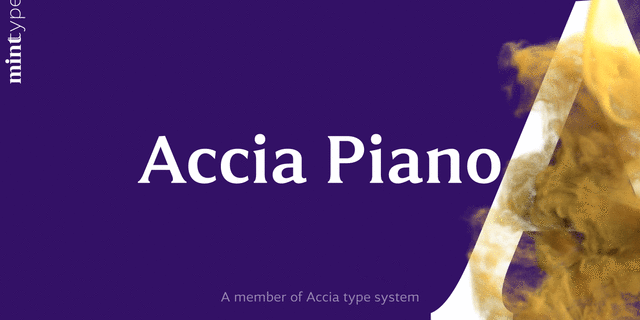
Accia Piano – спокойная, дружелюбная антиква. Его относительно короткие засечки, низкая контрастность и большая высота строчных отлично подойдут для газетных статей, а также для брендинговых проектов. Шрифтовое семейство содержит 8 начертаний от Thin до Extra Bold с соответствующими курсивами. Каждое начертание имеет обширную языковую поддержку, включая кириллицу, а также многочисленные функции OpenType: капитель, лигатуры, несколько наборов цифр, пунктуация с учетом регистра, дроби и индексы. Accia Piano является частью супергарнитуры Accia, куда входят пять шрифтов, от гротеска до выразительной антиквы. Это дает вам возможность проектировать максимально сложные серии продукции или информационные системы. Система Accia состоит из Accia Sans, Accia Flare, Accia Piano, Accia Moderato и Accia Forte. Гарнитуру разработал Андрей Константинов в студии Mint Type в 2021 году.
тонкий, худой, утонченный, деликатный, легкий, модный, качественный, культурный, отборный, благородный, гармоничный, элитный, дорогой, роскошный, красивый, мастерский, знаменитый, оригинальный, богатый, городской, прозрачный, острый, элегантный, ювелирный, эстетичный, изящный, художественный, драгоценный, гламурный, динамичный, комильфо, сексуальный, вежливый, эффектный, выразительный, характерный, прекрасный, аристократичный, исторический, традиционный, уникальный, ностальгический, светский, интересный, гуманитарный, яркий, королевский, пафосный, имперский, артистичный, каменный, легендарный, резкий, гордый, убедительный, твердый, устойчивый, авторитетный, звонкий, праздничный, сильный, героический, мотивирующий, заметный, броский, фундаментальный, торжественный, эпический, амбициозный, римский, властный, зрелищный, грандиозный, великий, величественный, монументальный, уверенный, архитектурный, кинематографичный, христианский, вкусный, аппетитный
серебро, роскошь, АСМР, красота, мода, ювелир, музыка, ресторан, комильфо, гламур, инстаграм, украшение, дизайн, часы, бутик, духи, премиум, отель, гостиница, шоколад, драгоценности, сервировка, опера, театр, музей, история, литература, искусство, художник, золото, живопись, костюм, галстук, парикмахерская, культура, проза, десерт, геральдика, эпос, мемориал, памятник, надгробие, скульптура, король, меч, антиквариат, карты, чай, архитектура, еда, алкоголь, коньяк, краска, банкнота, монета, конфеты, кофе, приключения, игра, виски, трофей, награда, замок, деньги, детектив, правосудие, власть, суд, император, архитектор, обед, ужин, кино, сыр, легенда, компьютерная игра, Библия, кафе, обувь, бар Стилистика: